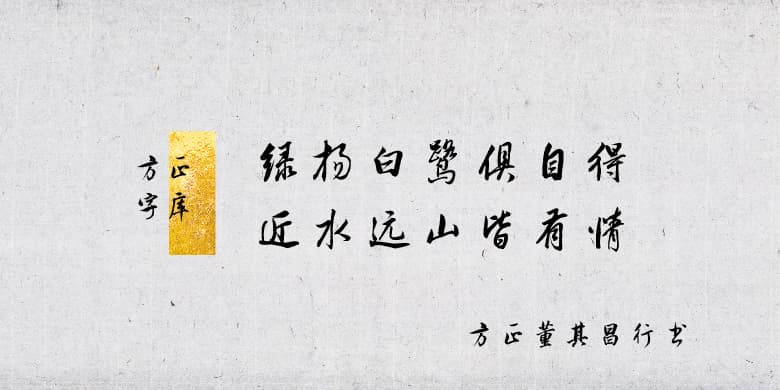
品牌:方正字库中华精品字库设计师:应立博,杨龙龙发行时间:2021字库编码:大陆简体(GB2312-80)分类:常规书写·毛笔字体属性:精品字
关于董其昌:
董其昌(1555~1636),字玄宰,号思白、香光居士。明后期大臣,曾官至南京礼部尚书与太子詹事,去世后获谥“文敏”。画擅山水,书法出入晋唐,自成一格,又颇能诗文。书画诗文传世佳作颇多。其书画风格与书画理论对后世亦颇具影响。
字体特征:
以董其昌书法作品《酒德颂》、《濬路马湖记》、《岳阳楼记》、《麻姑仙坛记》等书法作品为主要临创开发依据,并选用了大量的原帖字形,保留和延续了其笔画圆劲秀逸、平淡古朴及字体飘逸空灵、风华自足的特点。
临创者:应立博
整理/设计:杨龙龙、张全、韩文静、冯红晨、刘昱程、刘聪、孙睿、史通通、尚正中、田玄丹
审稿专家:刘洪彪、李有来、朱培尔、虞晓勇、邵佩英、张志庆、仇寅